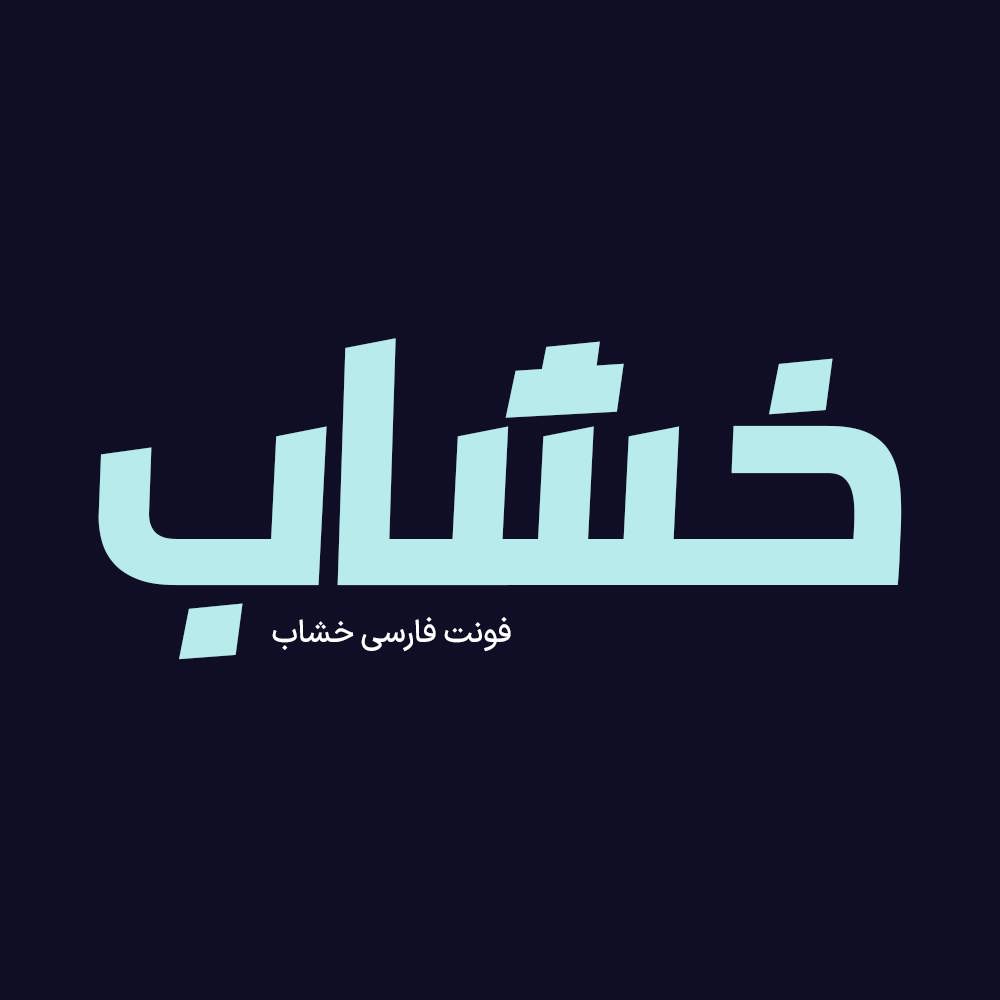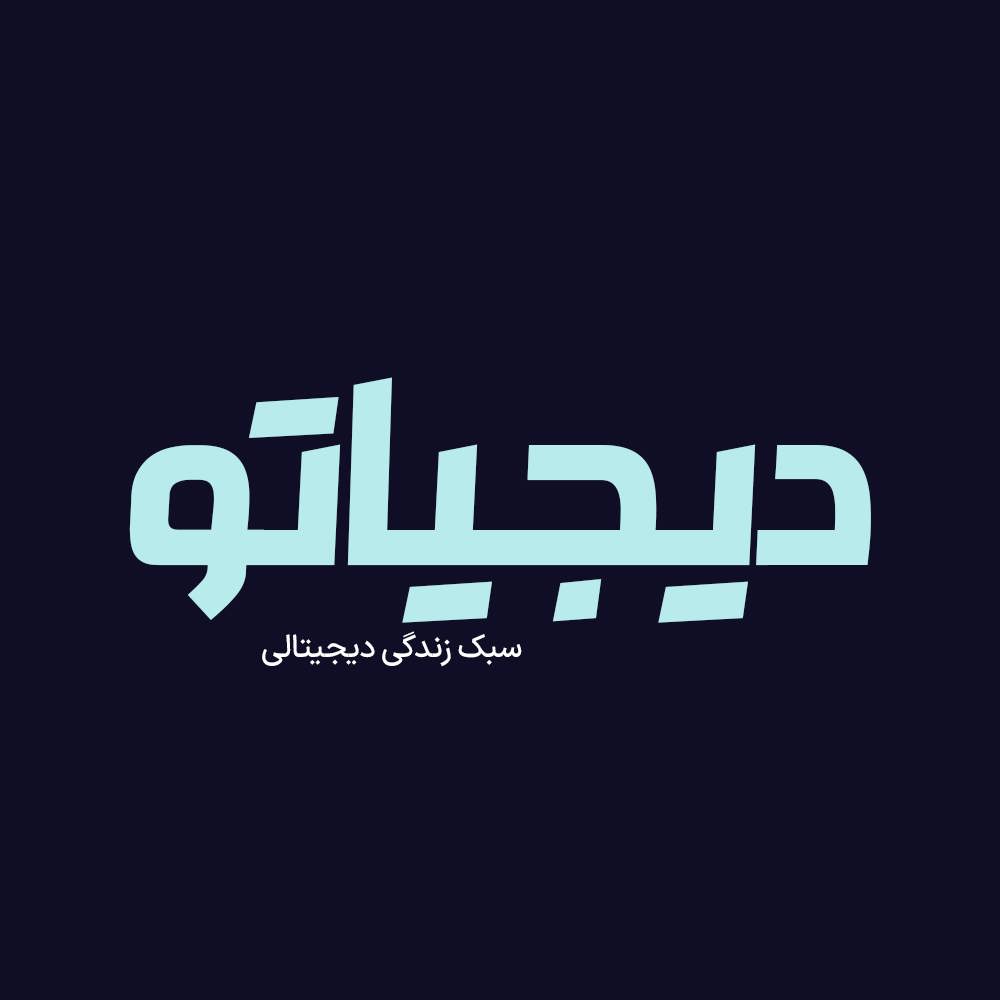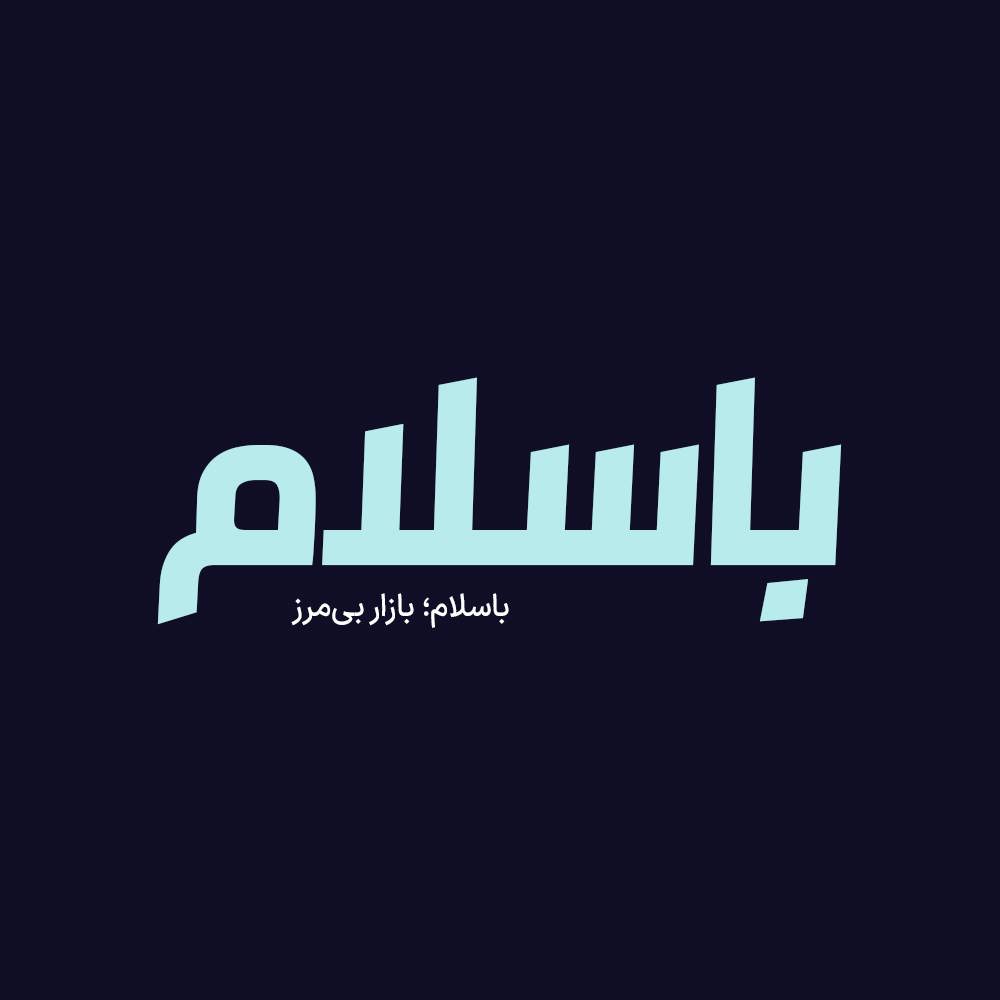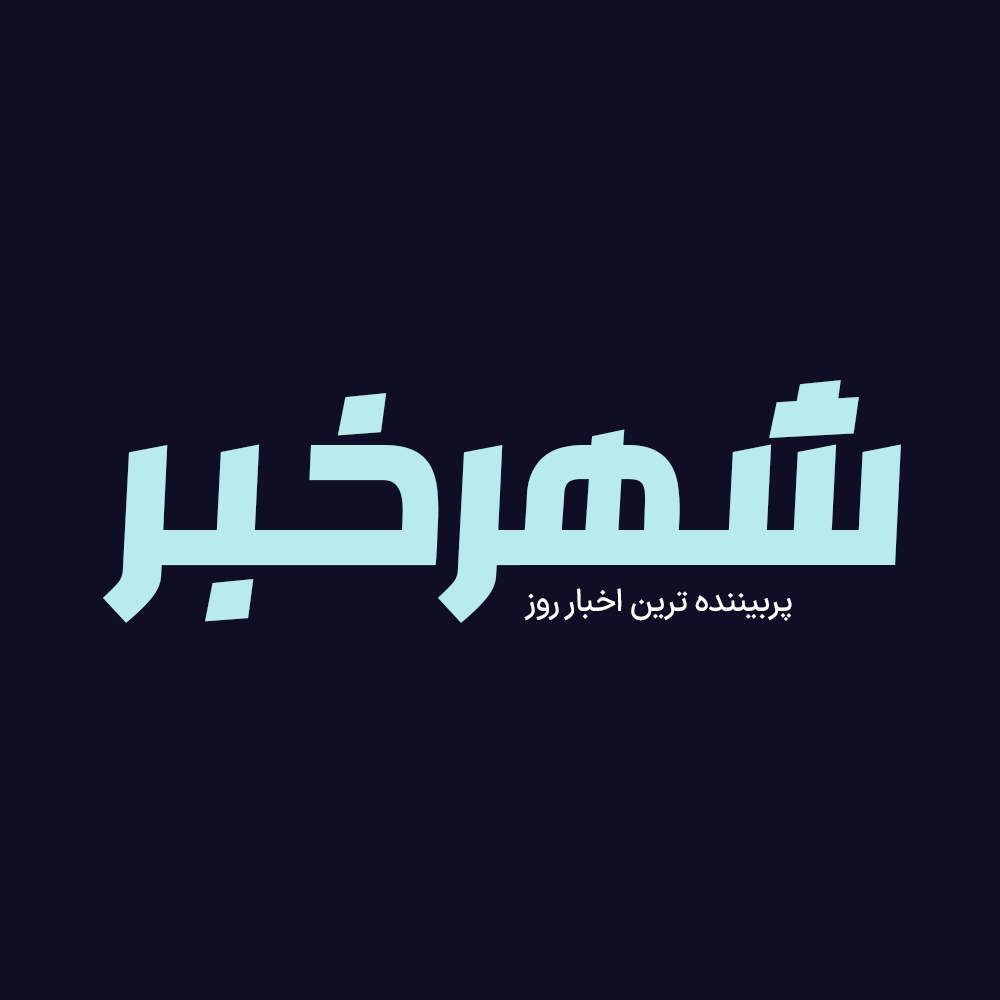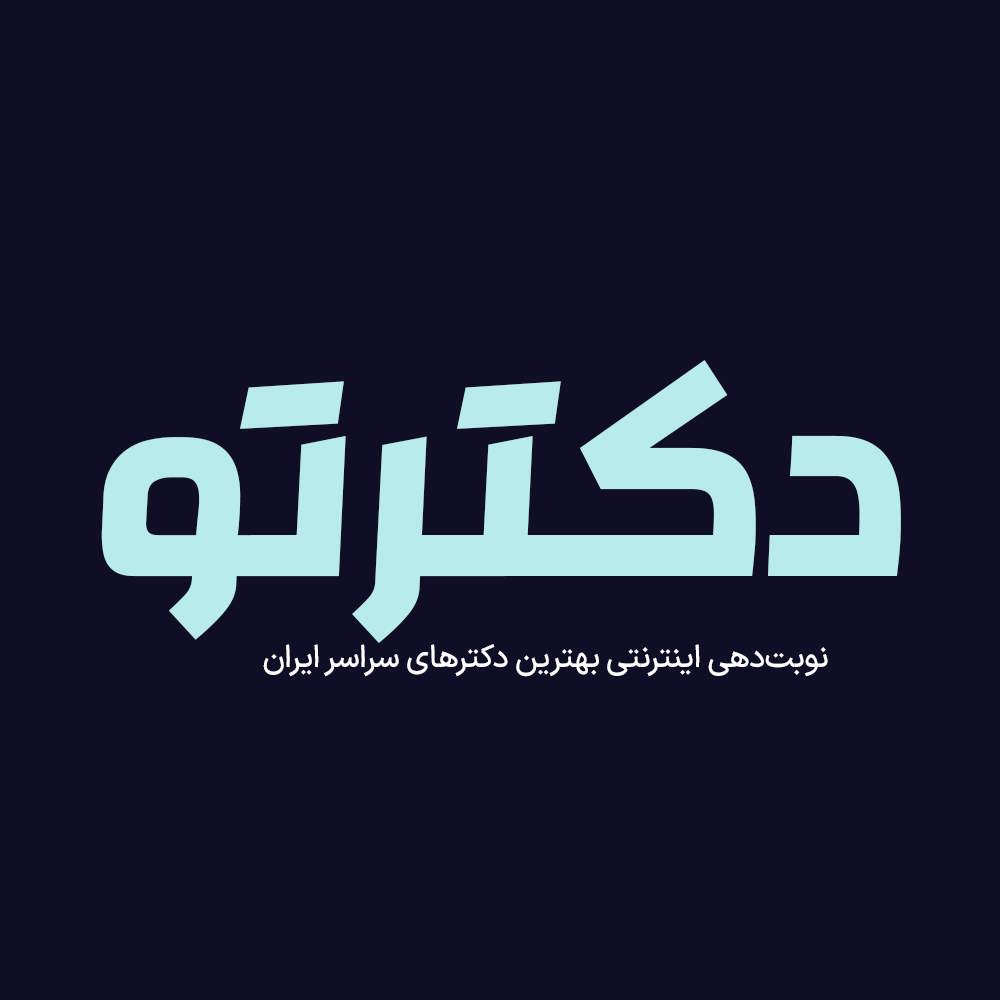
فونت فارسی خشاب Kheshab Font
فونت فارسی خشاب یک فونت تک وزن با کاربرد طراحی لوگوتایپ و طراحی های مختلف همچون کتاب و تولید محتوای متن های کوتاه و عناوین می باشد. این فونت با ساختار حروف خود مناسب استفاده در لوگوهای نوشتاری می باشد. فونت خشاب یک فونت عربی، فارسی سازی و بهینه شده است که برای طراحی انواع امور گرافیکی به خصوص طراحی انواع لوگوتایپ و تایپوگرافی می باشد. از آنجایی که فونت هایی عربی فاقد حروف “گچ پژ” هستند و مشکلاتی در تایپ حروف “ک” و “ی” دارند در فونت خشاب حروف “گچ پژ” و همچنین اعداد فارسی و انگلیسی اضافه شده است و نقطه های فونت و حروف “و” بازطراحی شده اند تا بتوانید تمامی متن فارسی را به وسیله این فونت تایپ کنید. در ادامه برای شما نمونه تایپ های این محصول حرفه ای رو آماده کردیم که میتونید مشاهده کنید.
پیشنمایش و نمونه تایپ های فونت خشاب